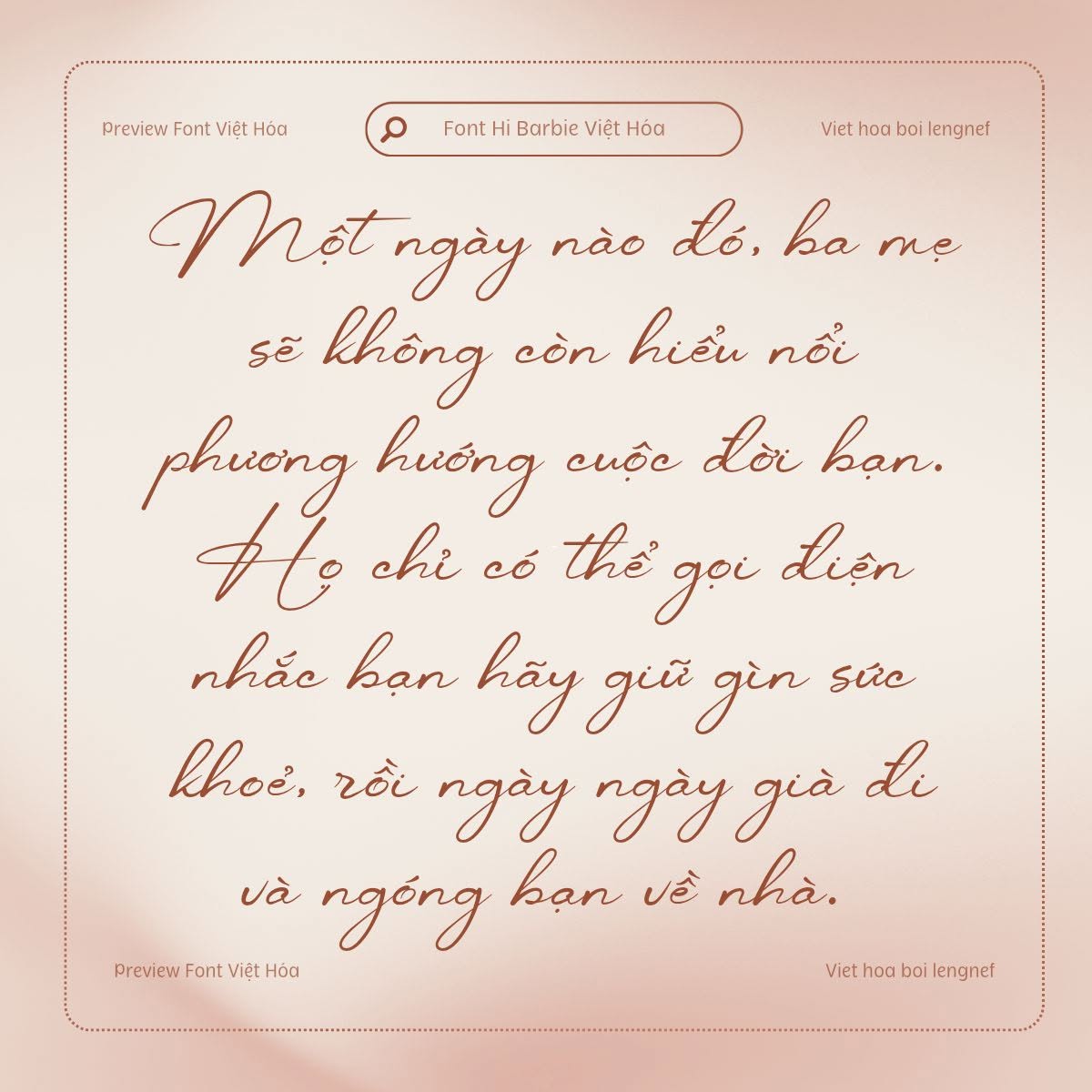
• Tác giả: Areatype
Font LF Hi Barbie Việt hóa
Hi Barbie là kiểu chữ viết tay hiện đại. Những nét uốn lượn sống động và đẹp mắt, có thể được sử dụng cho nhiều mục đích như tiêu đề, chữ ký, logo, thiệp cưới, bản tin, áp phích, huy hiệu, và nhiều hơn nữa.